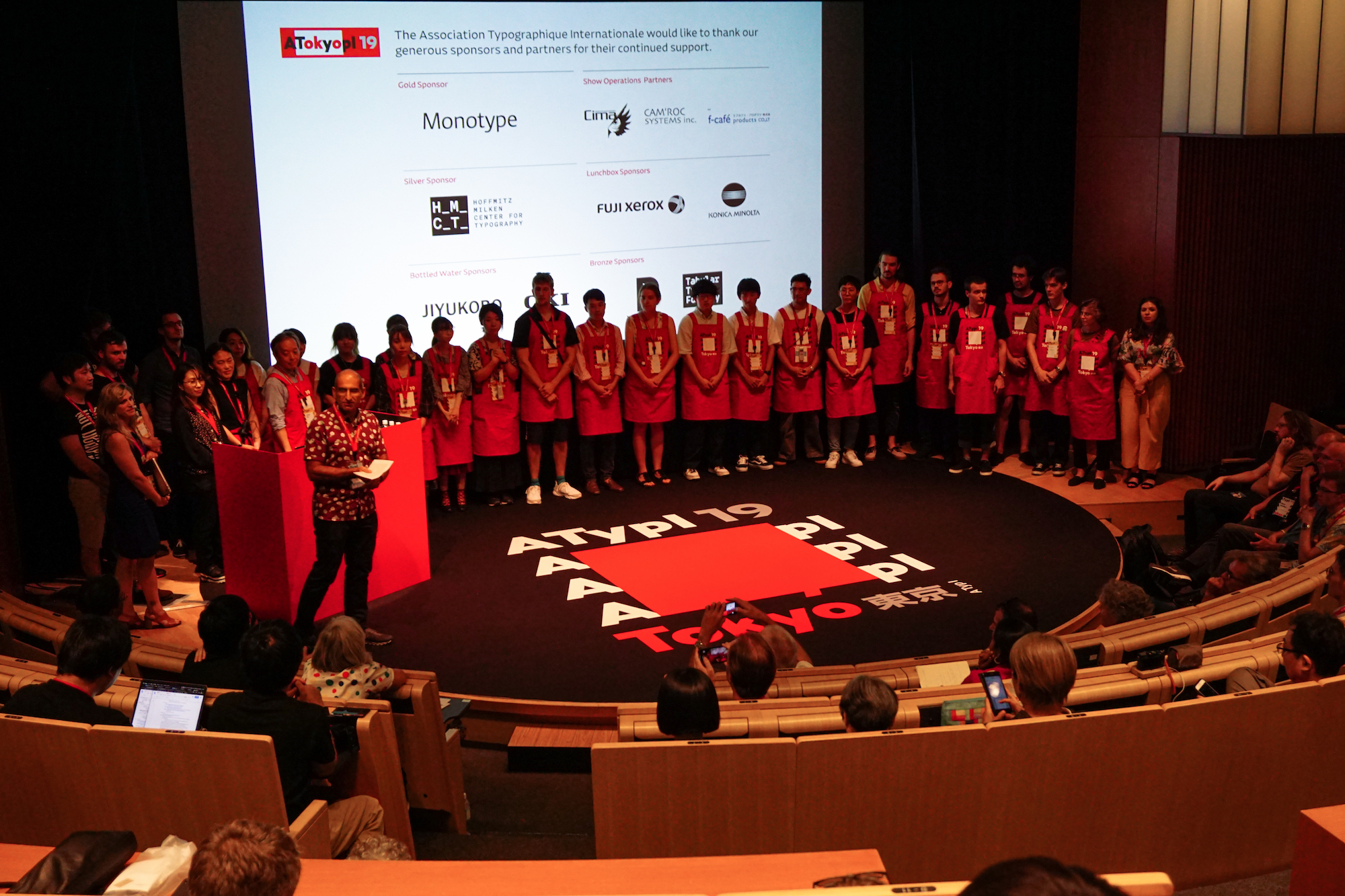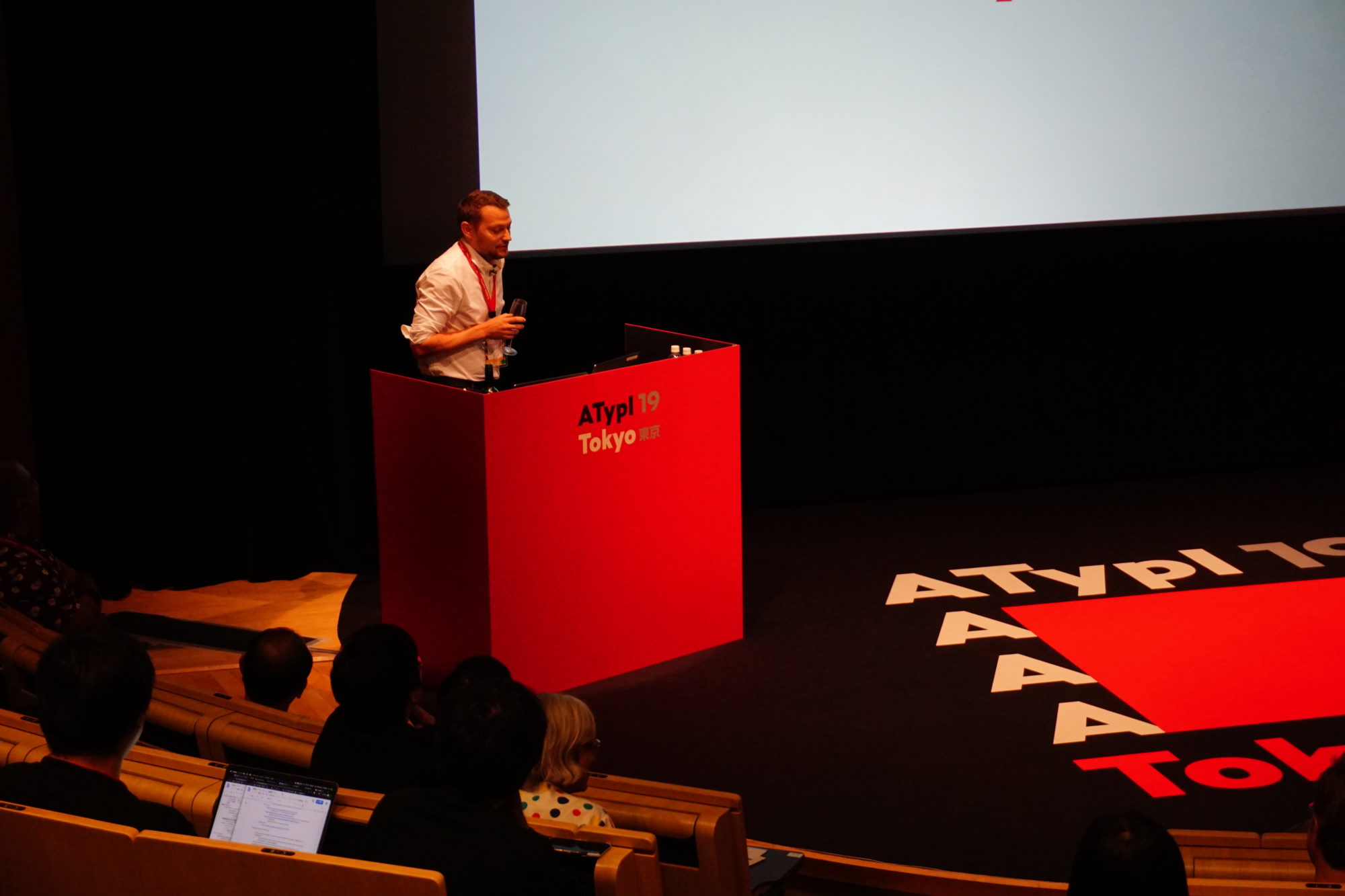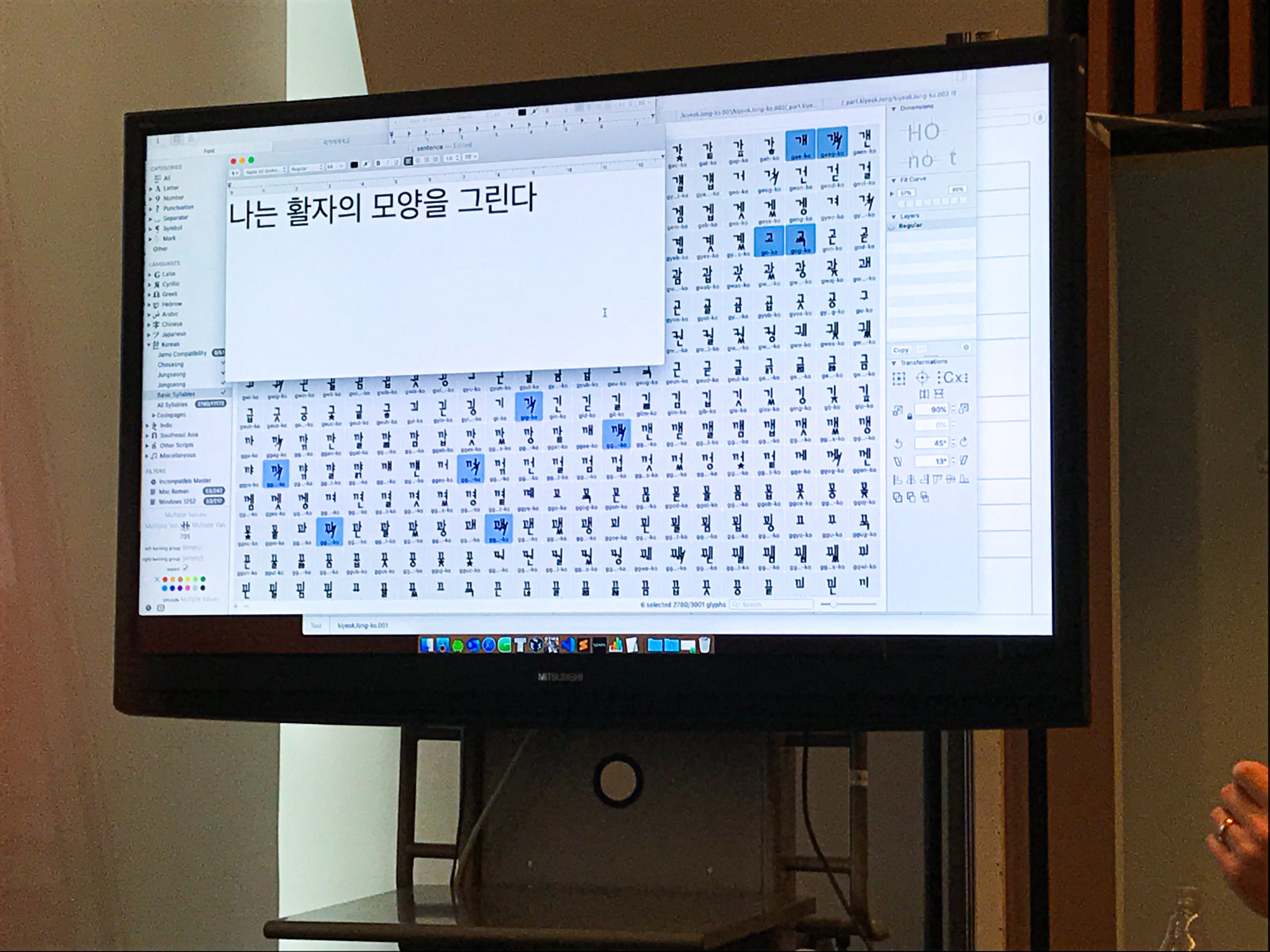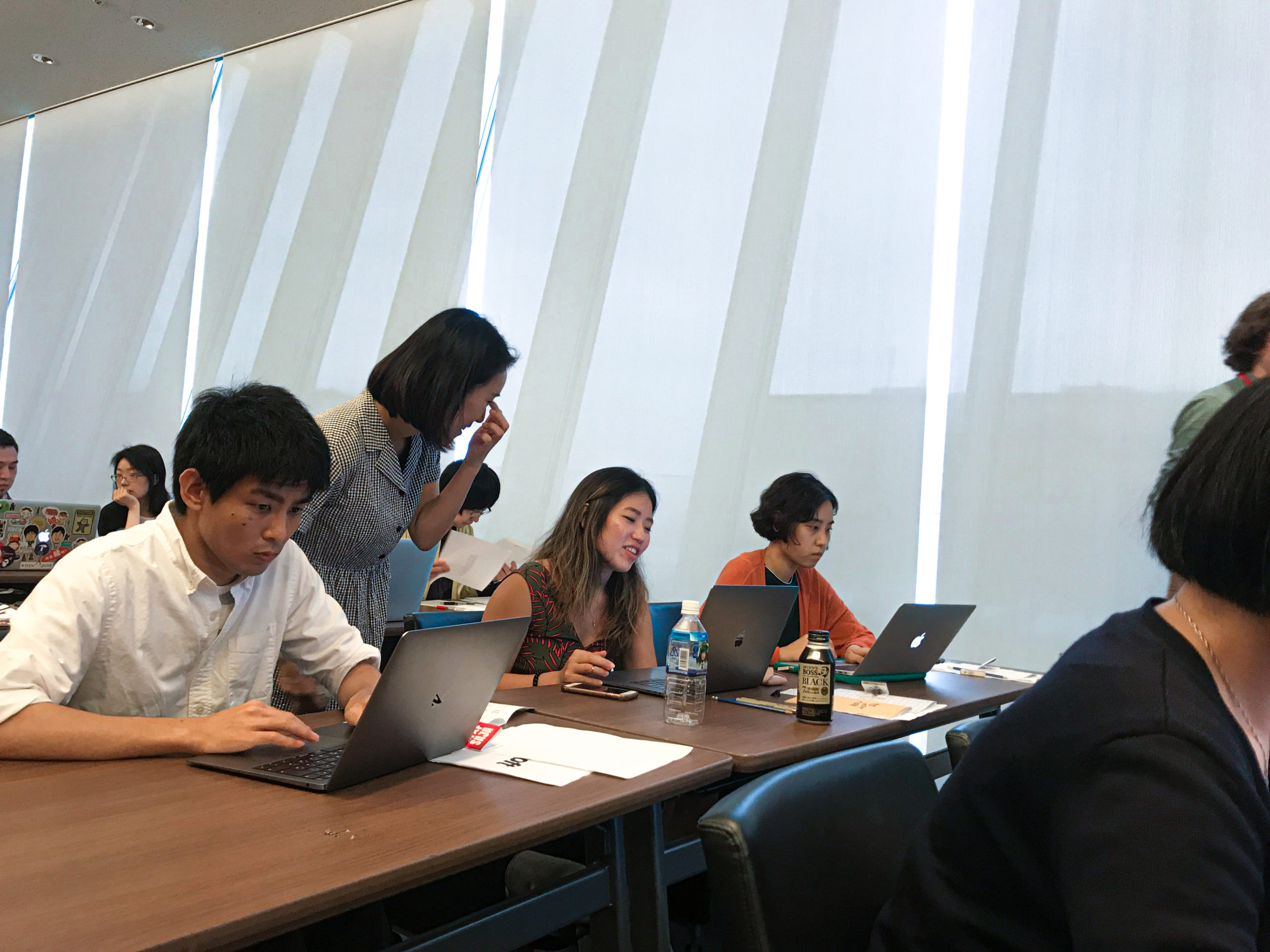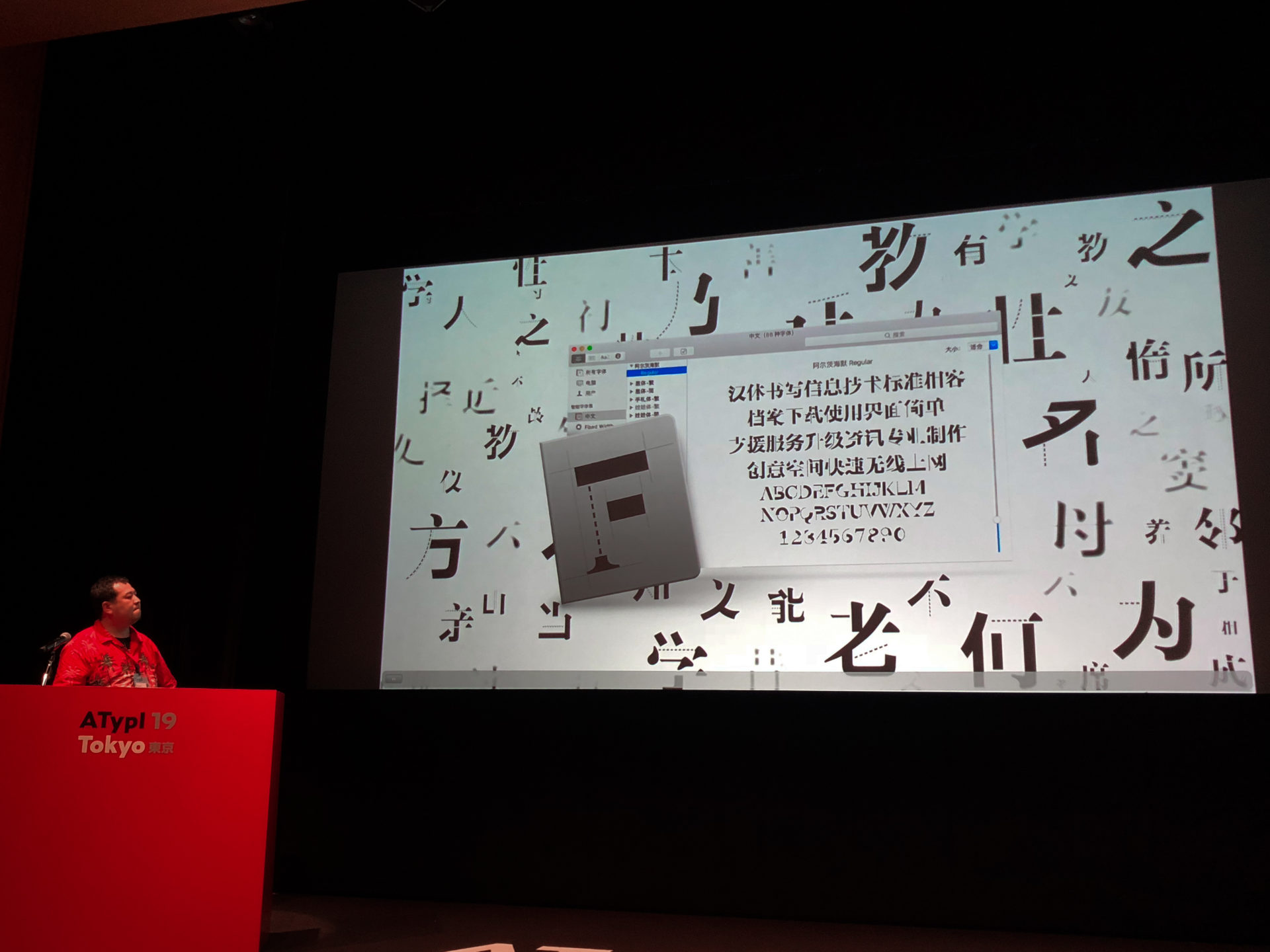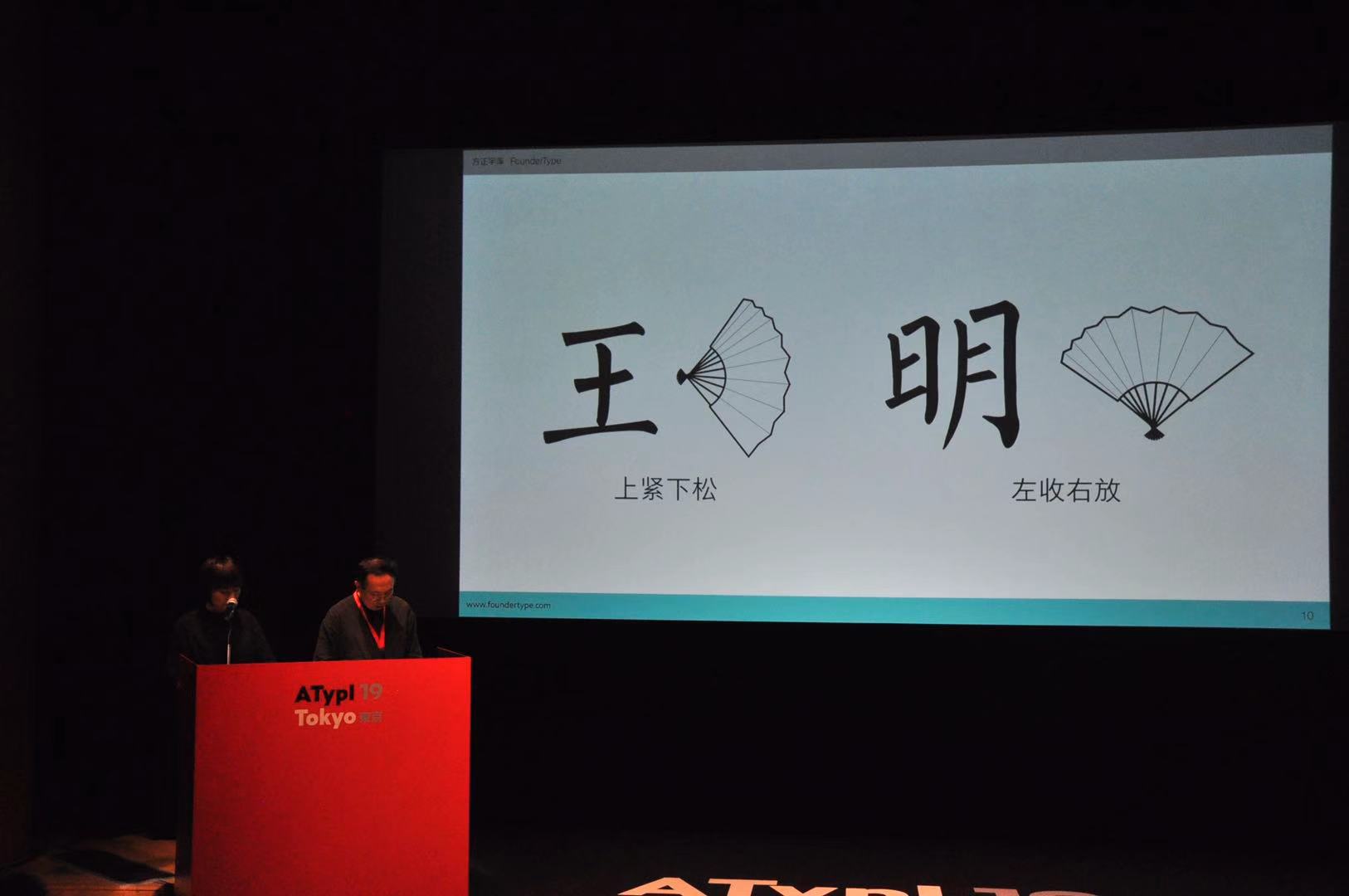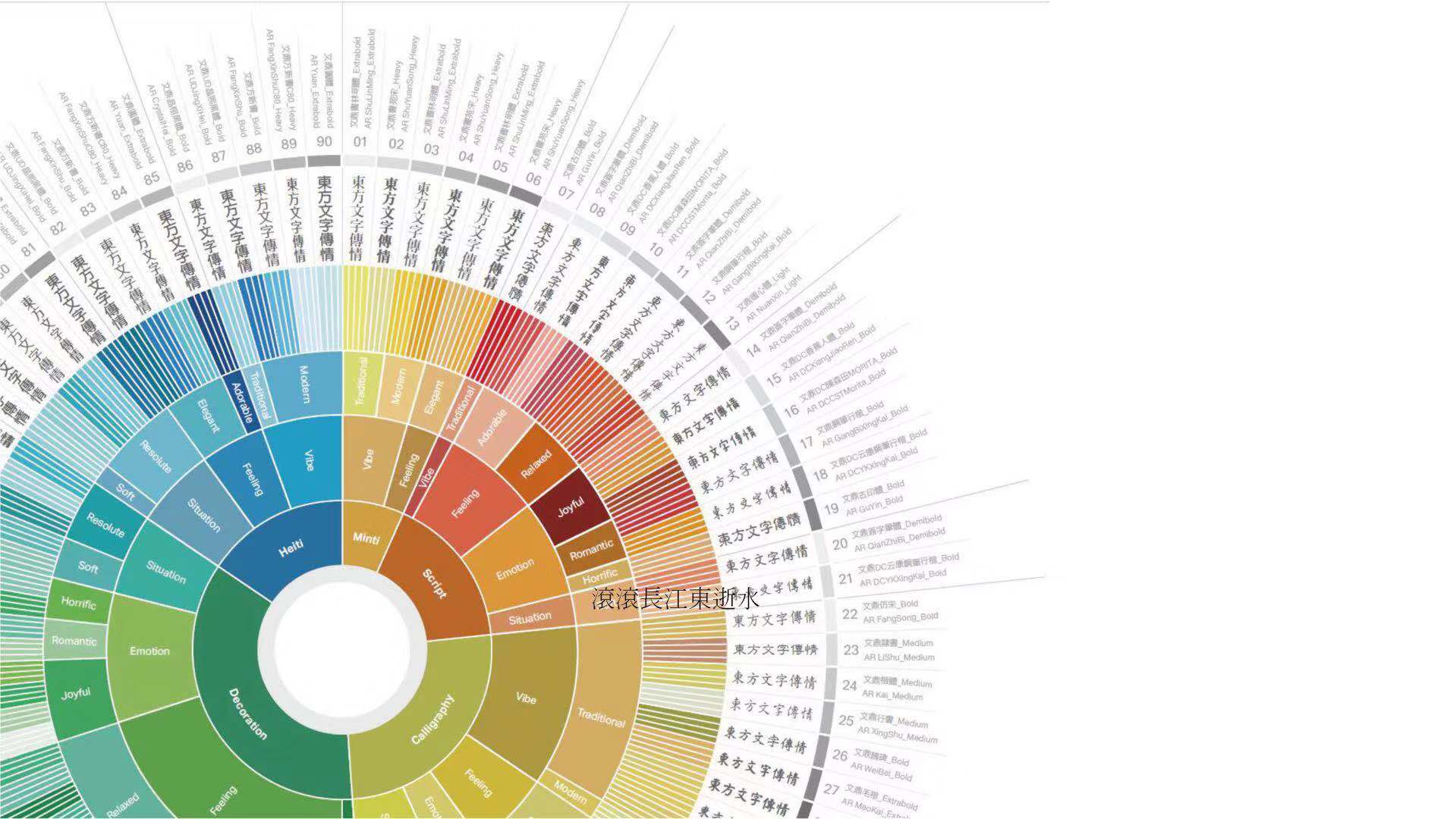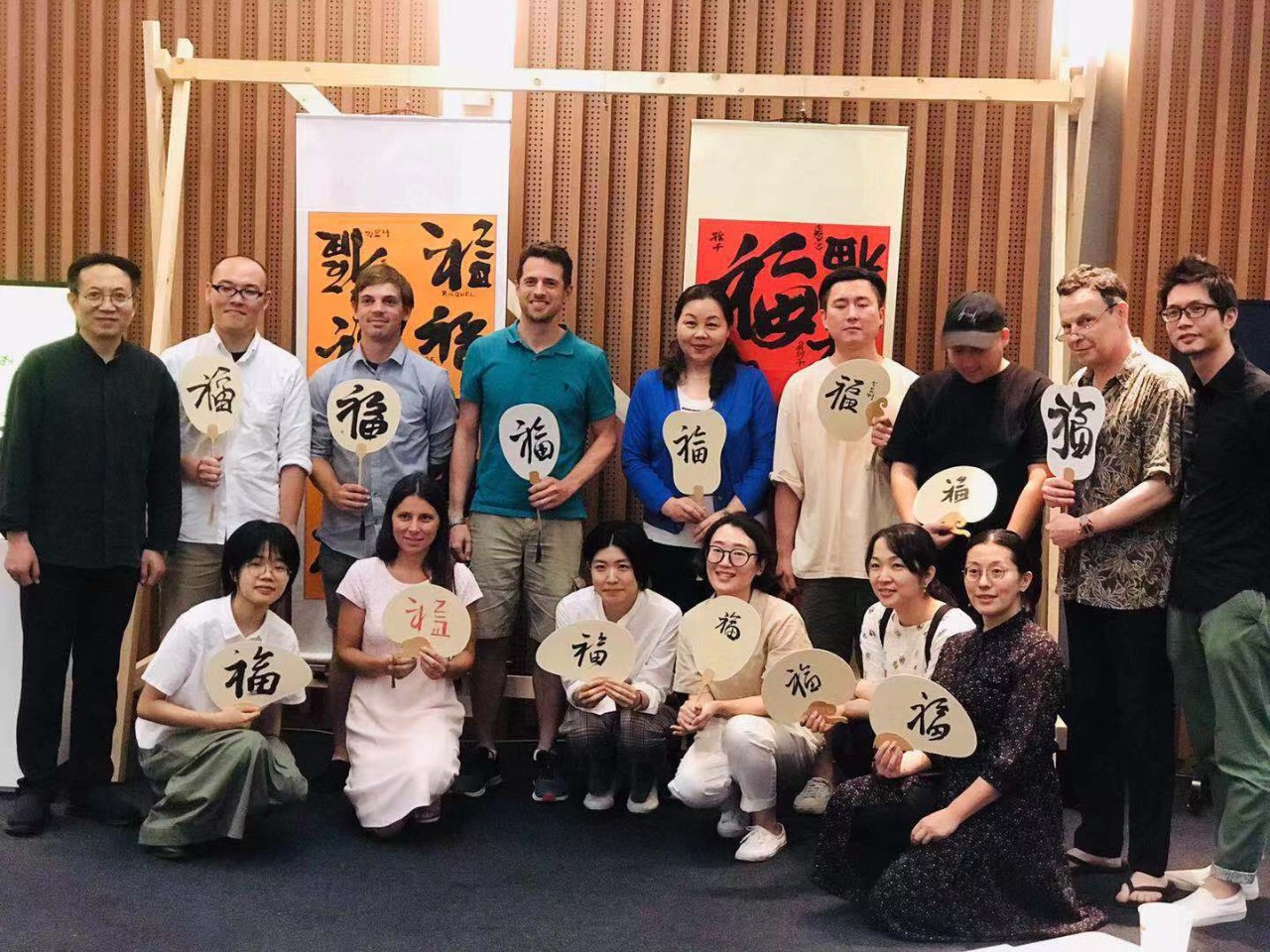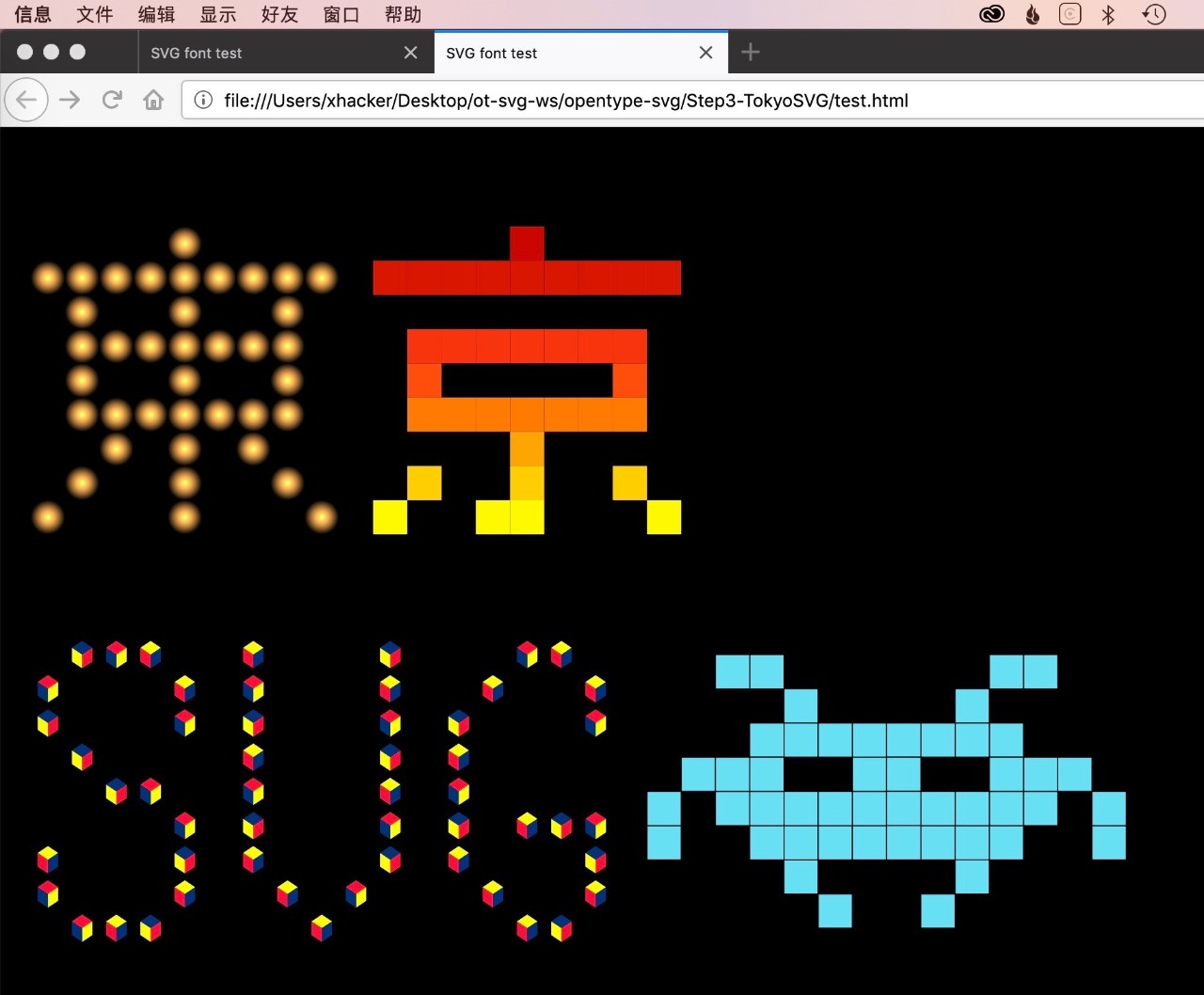
令和元年,字体之秋。2019 年 9 月 4 日至 7 日,国际字体协会(ATypI, Association Typographique Internationale)的年度会议时隔多年后再次来到亚洲,于东京召开。虽然每年在世界各地都会举办各类字体设计大会和设计节,但拥有六十多年历史的 ATypI 年会可以说是字体界一年一度最大的盛事。字体设计师、平面设计师、文字设计与文化历史的研究者、各大厂商、设计领域的出版商等齐聚一堂,各种形式的工作坊和来自各国代表的演讲让人应接不暇。
本站的编辑团队今年亲赴东京 ATypI 现场,在我们的微博和微信公众号平台上为中文圈的文字设计关注者带来每日的会程亮点速报。目前,ATypI 正陆续将演讲视频上传至官方 Youtube 频道,有能力的读者可前去一睹为快。不过,我们仍将之前在社交媒体平台上发布的每日报道整理在本页面上,作为视频导览和索引,同时也分享更多演讲之外的其他活动。
ATypI 工作坊集锦
ATypI 的第一天会程没有正式演讲环节,而是在各个会场同步进行的全天或半天工作坊,晚上则是开幕酒会和主旨演讲。
可变字体的响应式动态排版
当今字体界最炙手可热的莫过于可变字体(Variable Font)了,本次 ATypI 邀请到了可变字体排版专家 Jason Pamental,通过一整天的工作坊,为大家详细讲述可变字体动态排版的无限可能性。
上午,Jason 首先为大家介绍了使用可变字体的响应式网页排版效果:拖拽浏览器窗口,改变网页大小,字体的字重、宽度乃至对比度都可以改变。作为 W3C 专家的 Jason 随后介绍了诸多使用 CSS 进行网页排版的小技巧,例如使用多个变量来控制标题与正文之间的比例关系,而非写成固定的大小。虽然设计师并非一定要学习网页技术,但毕竟网页设计面对的设备环境千变万化,与传统平面设计的固定比例思路完全不同,需要设计师与开发者的通力合作才能保证设计的进行。下午,Jason 继续介绍 CSS 进阶技巧的同时,给大家展示了诸多可变字体的案例,例如通过 OpenType 特性,如何在网页中设置字体的不同可变轴,充分发挥出可变字体的魅力。
使用 Adobe Illustrator 和 Python Script 制作 OpenType-SVG 字体
除了可变字体,还有什么新技术值得一探究竟?日本字体开发者与设计师服部正贵和吉田大成向大家展示了字体与代码结合的力量——使用 Adobe Illustrator 和 Python 制作五彩斑斓的 SVG 字体。
Adobe 的高级工程师服部正贵首先为大家展示了许多有趣的 SVG 字体案例,以及如何用 Python 立刻制作 SVG 字体的各种酷炫效果。Adobe 的字体设计师吉田大成则展示了他基于 ATypI Tokyo 主题创作的设计样例,无论是像素风格、彩色渐变、还是浮雕造型的字体,在 SVG 字体里都能轻松实现。在工作坊中,与会者在自己的电脑上实际操作 Python 与 AI,纷纷制作出自己的 SVG 字体并在浏览器中成功显示。
从ᄀ到ᄒ:韩字设计入门
泛 CJK 的多语言设计一向是亚洲字体设计师关注的焦点。本届 ATypI 开设了韩字设计入门的全天工作坊,邀请的是擅长韩字设计的字体设计师 Aaron Bell 和来自韩国 Sandoll 字体公司的设计师 Chorong Kim,为想要初学韩字设计的设计师提供一个入门之道。
Aaron 首先介绍了韩文字母和文字的构成、韩国文字改革发展的历史、常见的书写风格及各自特色,以及文字结构的分类和比例规则参考,让学员抄写练习,熟悉其笔画和笔顺,并且与手写体比较区分。随后大家开始做上午的小作业:根据著名品牌的英文标识,定制符合其风格的韩文标识。对于非母语者来说,手绘过程中浮现了许多细节问题,比如「这样写会不会太奇怪」「这个笔画是否认得出来」等等,也是在培养对文字的感觉。下午则是开放式工作坊的环节,Aaron 介绍了用 Glyphs 制作韩字字体的工作流程,大家则根据自己感兴趣的方面,自由尝试练习和提问。由于韩字是由表音字母组成的字块,在 Glyphs 软件中可以通过智能部件以及 Hangul Composition Group 参数的配合,在制定完笔画与结构规则后,自动批量拼装成韩字字符。这一技术也引起了大家强烈的兴趣和热情。
中国书法
由方正字库提供的中国书法工作坊,15 个学员名额在前一个月即被一抢而空。虽然担任主讲的方正字体总监仇寅老师曾多次在国外举办过这样的工作坊,但此次大会在同为汉字文化圈的日本召开,因此也吸引了好几位日韩设计师的参与。学员们上午用水写字帖体会软笔的运用,下午则在临写「福」字之后开始自己的创作。学员们在短短六个小时穿越中国书法文化千年的轨迹,将自己对笔法、字法、章法的理解融入最后的共同创作卷轴中。我们的编辑 Eric 在现场担任中英和中日的翻译工作。
探索新的手写体
下午,来自捷克斯洛伐克的 Petra Dočekalová 带来了一场节奏紧凑的西文手写字体工作坊。致力于探索新的西文字体造型的她,使用不同的笔和道具,展示了四种手写样式,最后让大家创造属于自己的西文字体。
Petra 就读于布拉格艺术建筑设计学院,攻读字体设计博士学位,毕业设计便是探索新的西文字体手写造型。她为学员们准备了造型各异的手写字体样张以供参考,以及各种字体的描红练习,但同时她也教大家如何在这些字形基础上变化造型。学员们自由体验了各种宽头笔、酒精性海绵头笔等书写工具,为探索自己的书写风格作准备。最后的课题是基于教学来创写自己的西文字体,学员们使用了各种笔和道具进行创作。
字体与金钱的故事
精彩纷呈的工作坊过后,是开幕酒会和开幕演讲,赞助方日本字体公司森泽邀请到了 MIT Media Lab 主席 John Maeda 作开场辞。字体设计也许可以赚钱,但能靠字体设计来赚钱吗?John 从这个问题开始讲述了他自己与字体、设计与金钱的故事,独到的见解和老练的台风让现场高潮迭起。
ATypI 演讲亮点
从第二天开始,会议就进入了每天从早至晚十几场演讲连轴转的状态。当各位读者在官方 Youtube 频道回看所有演讲内容的同时,不妨配合我们的精选报道,了解重点和亮点。以下内容顺序较实际议程稍有调整,分别以日本文字设计、多语言多文字、字体技术、设计案例、设计研究与批评等主题来大致排序,方便大家浏览。
二十世纪早期的日本字体排印、美术字和商业艺术
Florence Fu(傅曦瑶)在旧金山的 Letterform Archive 档案馆做编辑助理。她通过研究 1928–30 年代滨田增治刊行的 24 卷《现代商业美术全集》,分析了当时日本商业领域文字设计的发展变化。
其一是美术字风格的变化,从传统的江户文字变化到新艺术风格、几何风格、装饰艺术风格、以及模数化镂版字等。其二是书写方向的变化,从清一色的从右到左竖排,到二战后逐渐出现横排,以及横竖混杂、日西文并置的状态。其三是使用字形的变化,在文字学的层面上,针对使用汉字、平假名和片假名,有了不同的主张。
战后两位设计师与现代主义
来自 Adobe 的山本太郎介绍了战后两位设计师清原悦志与 Helmut Schmid,并引出了战后现代主义的设计风潮。清原悦志是日本战后重要的平面与书籍设计师,代表作是《思潮》和 BLUE 等杂志。他常使用极端不对称的设计和极简的抽象图形,并坚持自我的风格。奥地利出身的字体与平面设计师 Helmut Schmid 在欧洲各国学习设计之后,来到日本大阪以独立设计师的身份开始活动。其代表作是 1980 年发售的 Typography Today。
江户时代的极粗字体
Type Project 的日文字体设计师石川朋子介绍了江户时代流行的三种极粗字体:「勘亭流」「相扑文字」和「提灯文字」。勘亭流用于歌舞伎的招牌或节目表,笔画婉转圆润。与之相对的,相扑文字虽然也是用特粗毛笔写成的,但笔画粗直有力,用于相扑对阵表中。提灯文字常见于饮食店门外的日式灯笼上,由细笔勾画轮廓然后填色而成,与前两种直接书写的文字不尽相同。石川提及极粗文字的流行趋势,尤其是在动漫、游戏和广告中。最后,她还介绍了 Type Project 基于名古屋这座城市设计的极粗字体。
三个角度,谈当代日文汉字设计趋势
日本字体协会此次邀请了三位德高望重的设计师从三个角度谈论汉字设计:片冈朗谈字体设计,高桥善丸谈 logo 设计,工藤强胜谈文字排版。
片冈朗是砧字体制作所的主理人,其特点是擅长设计圆体,代表作是丸明朝体、丸丸黑体等笔画松弛圆润的字体。片冈朗首先提出汉字对于日文字体设计的重要性:帮助日文表意。在计算机出现之后,由于在字体上加圆形笔画末梢相对方便,圆体应运而生。之后片冈朗以自己的明朝体和黑体作品为例,探讨了字体设计师的本质。日本字体协会会长高桥善丸带来的是 logotype 的设计分享。他提出了汉字 logo 设计的七个思路:依据网格、摆脱网格、化用图形、省略笔画、视觉形象、视觉联想和图像先行。书籍设计师工藤强胜分享了自己的作品中的汉字排版。在汉字假名并置的情况下,汉字主导意思功能,所以大小悬殊也不影响理解。在方向上,汉字的优势是可以横排或竖排,灵活的字体字形混排既是挑战,也是机会。
关于池原香穉:日本首批金属活字设计者
在日本,「活字之父」当属木本昌造莫属,但其实在这段历史中还有一个重要人物:为假名活字书写了手稿的池原香穉。设计师和学者春田女士的一个研究方向便是他的生平。
从江户时代到明治初期,日文假名经历了一段转变的过程,过渡时期的假名设计字型类似连绵体,但是是分开的活字,由木本昌造制造。池原香穉就是其中假名手稿的书写者,书法特点入笔很强烈,笔画有弹性,柔中带刚,中宫宽,重心低稳,整体圆润,弧形笔画多,十分符合日本人对假名的审美。除了书法造诣高,池原香穉同时还是一个多才多艺之人。例如他的本职工作是一名眼科医生,曾与荷兰人合作做过字体的视觉研究;还曾给二十多个地方报纸写新闻报头,并且沿用至今。
池原香穉的重要性在于,在没有铅字的时代他书写了适用于印刷的用字,并以广博的学识辅助研究了文字应该被如何阅读。虽然铸造金属活字的技术从西方引进,但池原香穉的贡献让我们意识到有许多重要的工作仍是由本土的艺匠来完成的。
一场剧变:日本 70 年代中村征宏的 Na-ru 和 Go-na 如何影响了日本字体设计行业
Monotype日本公司唯一一位字体设计师土井辽太介绍了日本七十年代中村征宏设计的两款超大中宫的字体,圆体ナール(Na-ru)以及黑体ゴナ(Go-na)。这两款字体在之前并没有数字化,所以默默无闻,但事实上在日本随处可见,出现在高速公路的指示牌上,或是机场的导视设计中。
中村征宏曾经是一名插画师,为电视台绘制各种片头字体标题字,后来在写研首次举行的字体比赛中用 Na-ru 字体成功获奖,并制作成照相排版字体。由于当时圆体字非常少见,Na-ru 刚一出世就获得很多设计师青睐。同时,Na-ru 字体的假名撑满字框,一改之前的变宽假名的设计,让排版师无需再剪切文字调整字距,竖排也非常整齐。就这样,Na-ru 很快遍布日本街头,影响了整个字体设计行业的面貌。
下一届 ATypI,法国见!
一场 ATypI 会议需要两年的时间来做充足的准备。2021 年的大会将在斯德哥尔摩举行,而明年 2020 年将在法国巴黎举办的 ATypI 的筹划工作已在进行中。法国筹委会的代表、Production Type 的设计师 Jean-Baptiste Levée 潇洒地举杯邀请大家共赴巴黎,享受字体设计的盛筵。我们也期待在明年为大家继续带来现场报道。